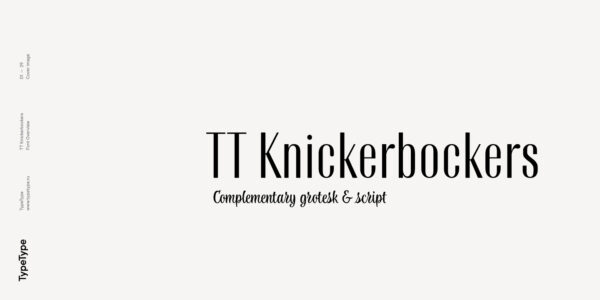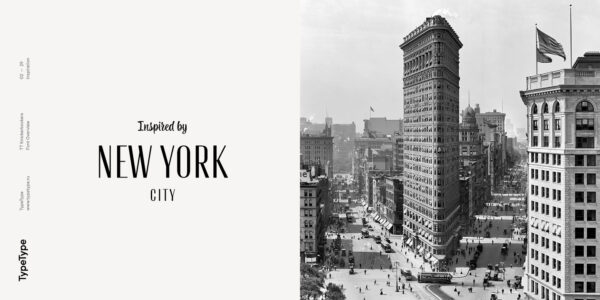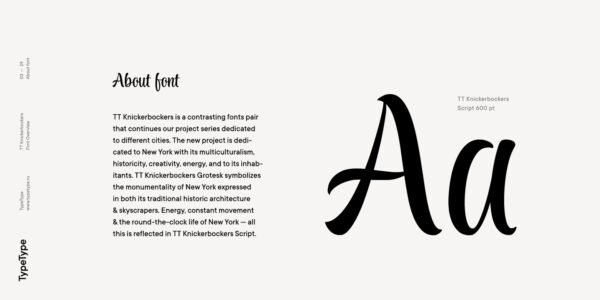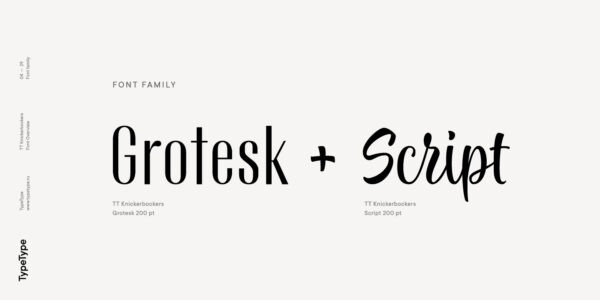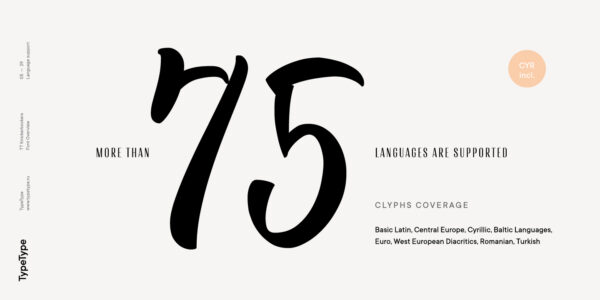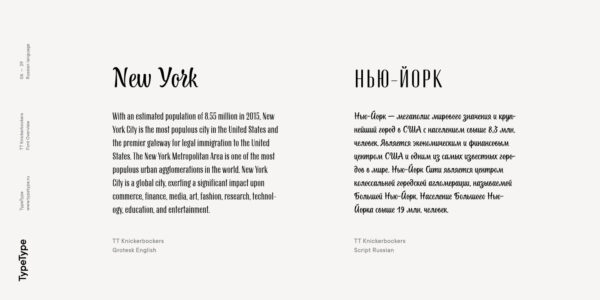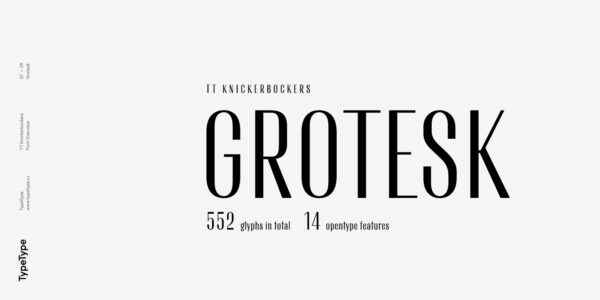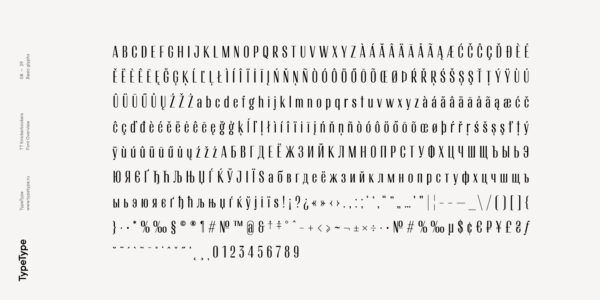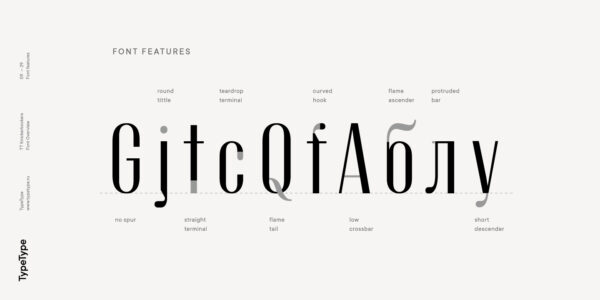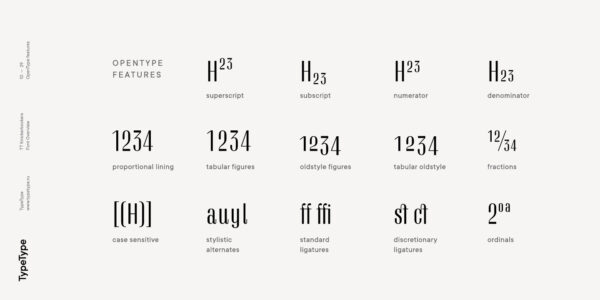
TT Knickerbockers
TT Knickerbockers — ТТ Никербокерс
Произносится «ТТ Никербокерс». «Knickerbockers» — производное слово от knickerbocker, в переводе с английского «никербокер». Буквы «TT» являются аббревиатурой названия компании.
TT Knickerbockers — контрастная пара шрифтов, посвящённая Нью-Йорку. Гротеск символизирует монументальность города, а рукописный шрифт — его энергию и постоянное движение.
О гарнитуре TT Knickerbockers
Поддержка языков 160+
TT Knickerbockers это контрастная пара шрифтов, продолжающая серию наших проектов, посвященную различным городам. Новый проект посвящён Нью-Йорку с его мультикультурностью, историчностью, креативностью и энергией, а также его жителям. TT Knickerbockers Grotesk символизирует собой монументальность, выраженную в как в традиционной исторической застройке Нью-Йорка, так и в его небоскрёбах. Энергия, постоянное движение и круглосуточная жизнь Нью-Йорка — все это отразилось в нашем TT Knickerbockers Script.
TT Knickerbockers Grotesk — это узкиий контрастный гротеск с характерными элементами отсылающие нас к 19 веку. В шрифте также прослеживается отсылка к антиквенным шрифтам — места традиционных антиквенных засечек в TT Knickerbockers Grotesk решены с помощью прямого окончания штриха, а в местах традиционного расположения капель мы сделали штрихи скругленными. В TT Knickerbockers Grotesk вы найдете необычные знаки, стилистические альтернативы, лигатуры. В шрифте использованы следующие OpenType фичи: ordn, case, frac, sups, sinf, numr, dnom, onum, tnum, pnum, liga, dlig, salt, ss01.
Идея TT Knickerbockers Grotesk базируется на дипломном проекте Надежды Поломошниковой.
Иван Гладких — руководитель проекта
Юлиана Моргун — дизайнер рукописного шрифта
Наджеда Помломошнова — дизайнер гротеска
Филипп Нуруллин — шрифтовой дизайнер
salt | Stylistic Alternates
alуu
liga | Standard Ligatures
fl ft ffi
dlig | Discretionary Ligatures
ij ct st
onum | Oldstyle Figures
1638
case | Case Sensitive Forms
({[H]})
numr | Numerators
H123